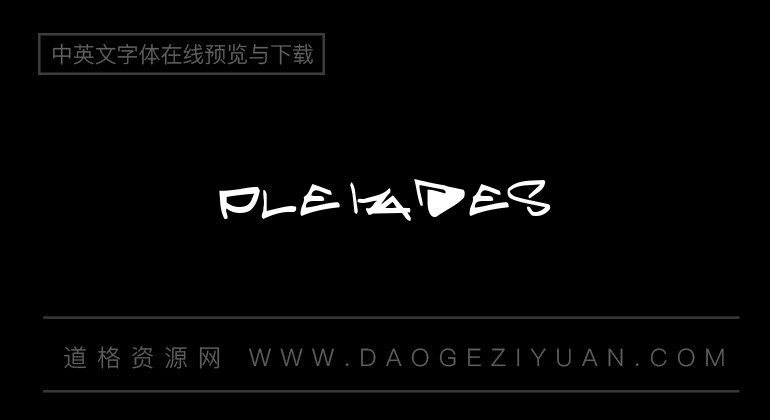
Pleiades 是一款非常流行的手写字体,特点是流畅、优美、清晰易读。该字体的风格非常适合在设计中用于标题、徽标、标语、海报、卡片等方面,特别是在需要加入个性、温暖、人性化的设计中更是不可或缺的。 Pleiades 字体家族由 7 种不同粗细的字重和 3 种字体风格组成,包括黑体、细体和两种不同的斜体。此外,该字体还带有多种字形变体,包括连字、省略号、符号和数字。 Pleiades 字体由加拿大设计师 Michael Mervinetsky 制作和发布,最初发布于 2015 年。该字体的设计灵感来自于手写体,在保留手写字体的独特个性和魅力的同时,又具有数字化字体所具有的优点,如清晰易读、一致性和可扩展性。内容介绍
Pleiades是一款非常不错的手写艺术字体,具有很好的视觉感,适合于文化类的宣传设计、商业类品牌的广告和产品包装设计以及个性化文字排版等较多场景。